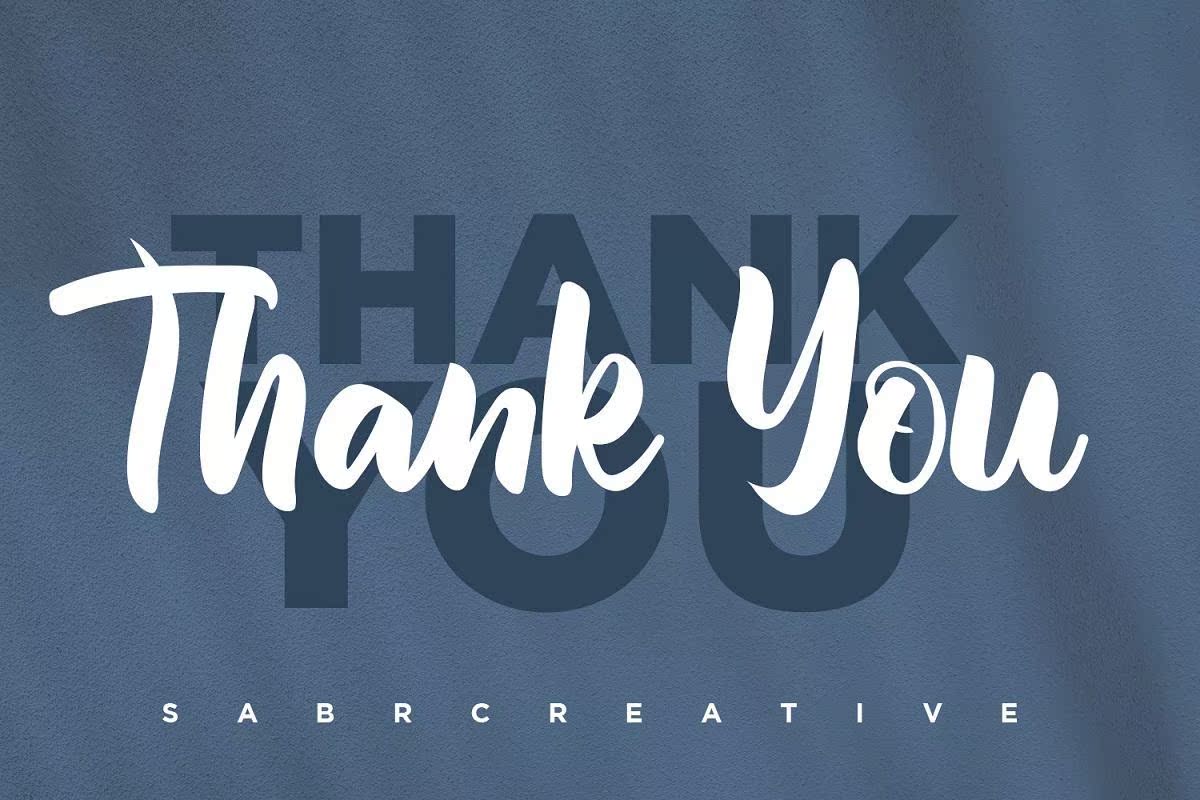
FreeKalyubiscriptFont是一款出色的SwashScriptFont。您可以在名片、婚礼庆典、传单、报纸、杂志、广告横幅等多个方面查找您的作品。这款令人印象深刻的Font来自一个格式文件,您可以方便地安装和使用您的设备。该设计基于全球趋势创建此Font,Henceitlooksverygood and professional。但是,这种自由方仅适用于个人许可证使用。但是,不要担心,您还可以通过购买PremiumVersion获得更多功能。